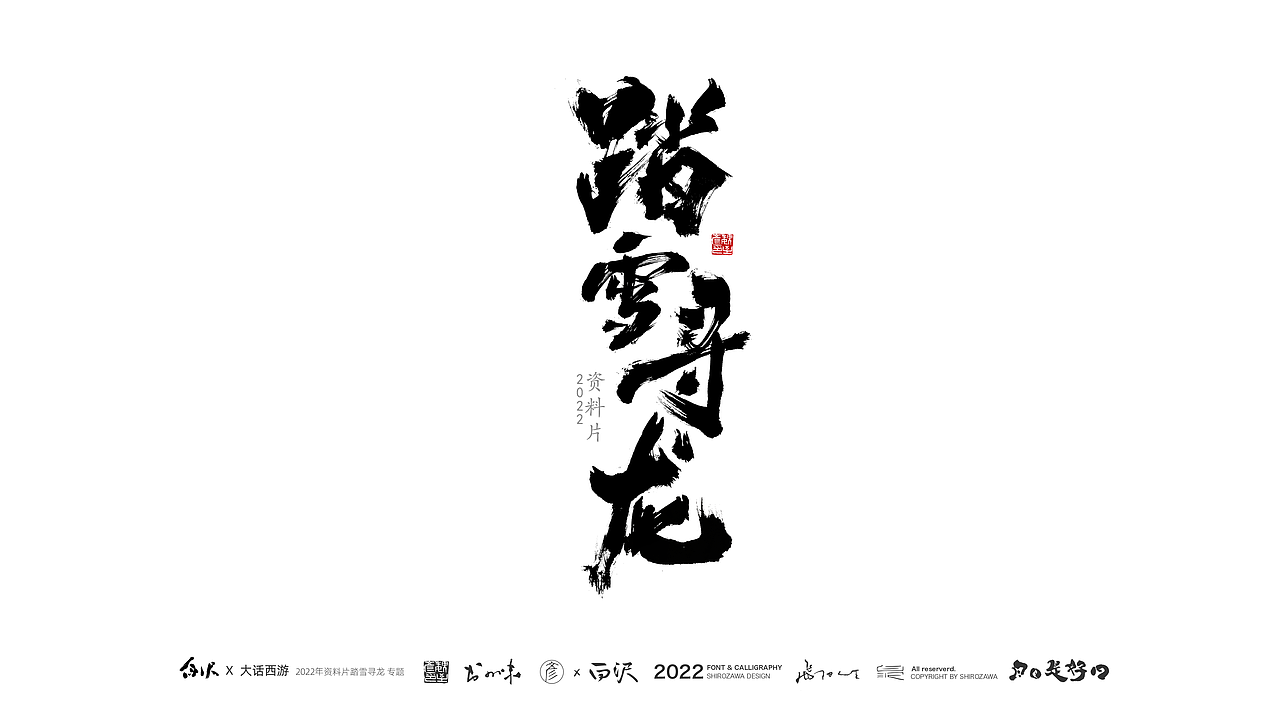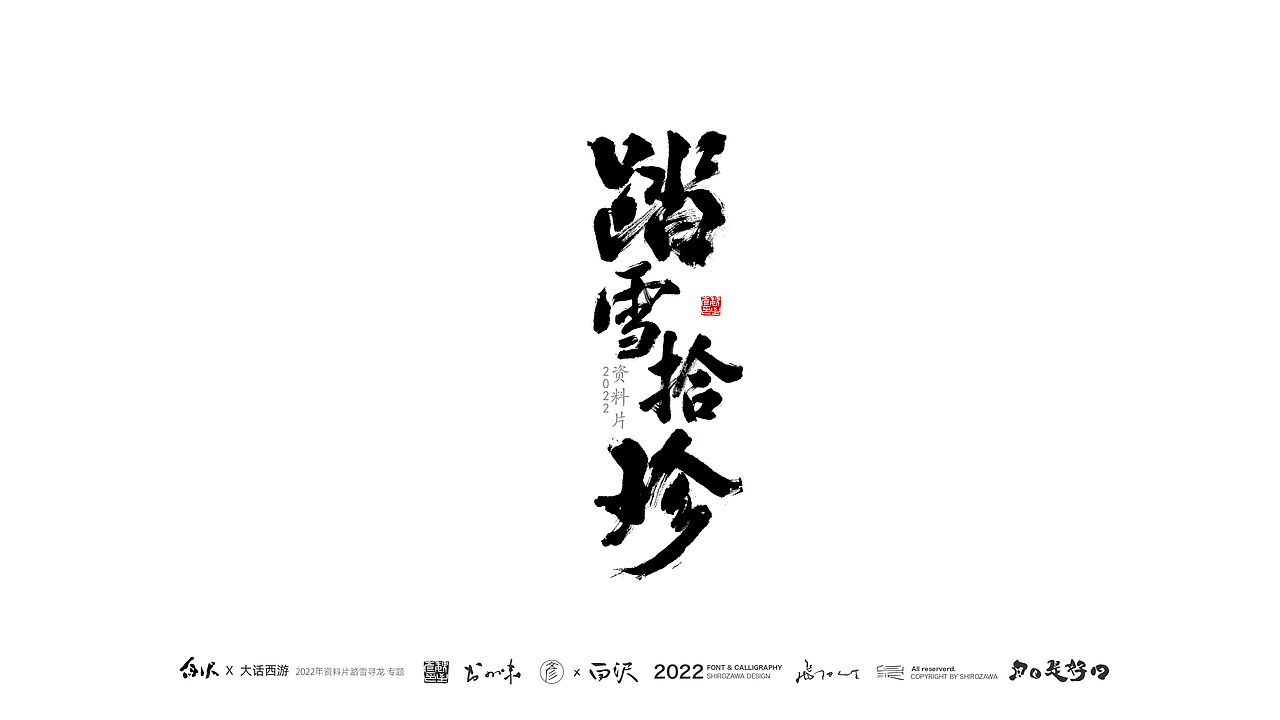
手游「大话西游」资料片·书法字体设计
去年年底完成了「大话西游」手游 踏雪寻龙专题的书法字体设计(「踏雪寻龙」、「上古应龙」、「百人斩龙」、「帮派集结」、「踏雪拾珍」)。
参考了许静老师的「悬崖之上」,打磨了一个多月。
要在约束规矩内发挥出自己的特点,五组字要使用相同的排版,但是这些字结构的特点又不尽相同,非常考验结体的功底。
需要的风格是“上古感”而不是“江湖感”,微妙的差别让我思考了很久很久。
好在合作的小伙伴们都非常专业,磨合沟通过程让我受益匪浅,最终一起完成了这组字的设计。